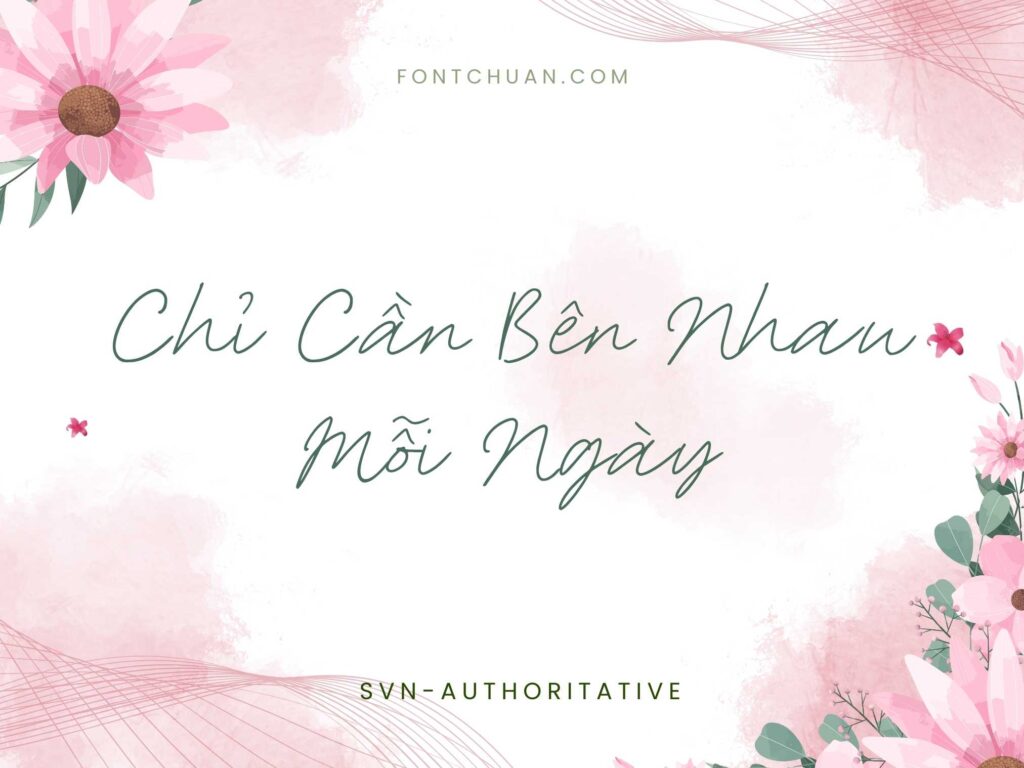
Font SVN Authoritative Việt Hóa
Authoritative là một font chữ viết tay tự nhiên, được thiết kế bởi Agam Rahmadan và phát hành bởi Viswell. Font này được tạo ra với các nét viết tay tự nhiên, phù hợp cho việc sử dụng trong thương hiệu, trích dẫn, logo, văn phòng phẩm, thủ công và nhiều hơn nữa. Font đã được Việt hóa để hỗ trợ tiếng Việt bởi Styleno.1 Fonts, đồng thời hỗ trợ nhiều ngôn ngữ khác, giúp mở rộng phạm vi sử dụng trên toàn cầu. Font này được thành viên của Font Chuẩn sưu tầm và chia sẻ, đáp ứng nhu cầu của bạn đọc và ứng dụng thực tế vào các dự án thiết kế.
Đặc điểm thiết kế của Authoritative bao gồm các nét viết tay tự nhiên, tạo cảm giác chân thực và gần gũi. Font này phù hợp cho các ứng dụng như thiết kế thương hiệu, trích dẫn, logo, văn phòng phẩm và các dự án thủ công. Các ngành nghề phù hợp bao gồm quảng cáo, nghệ thuật và thiết kế đồ họa.